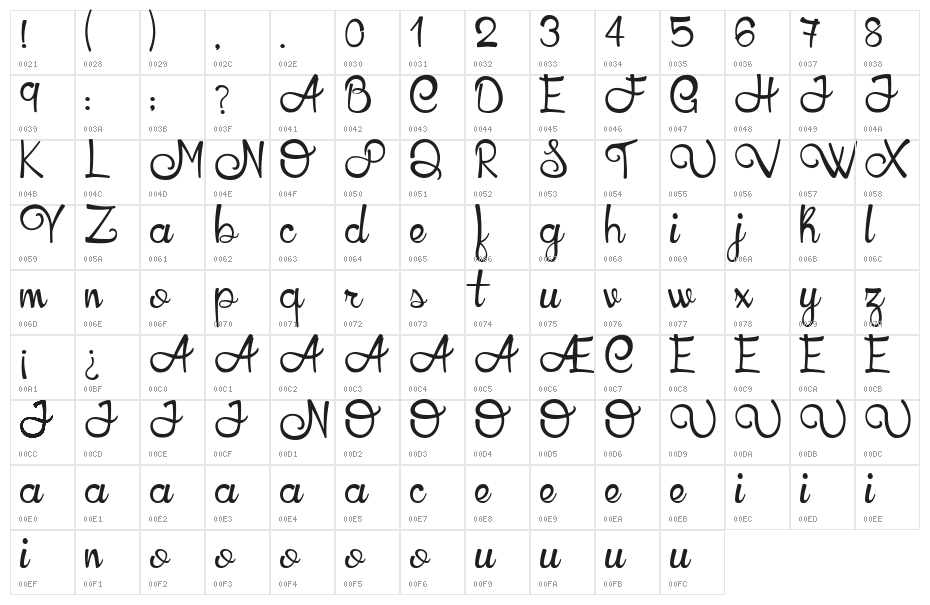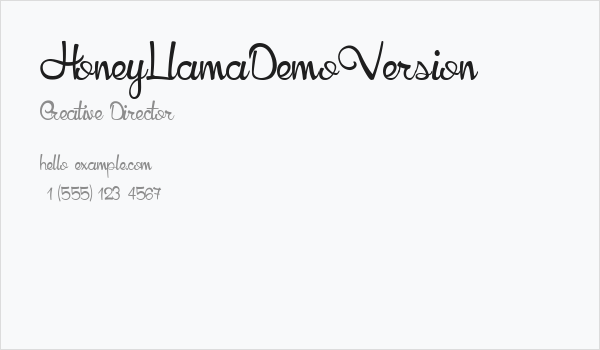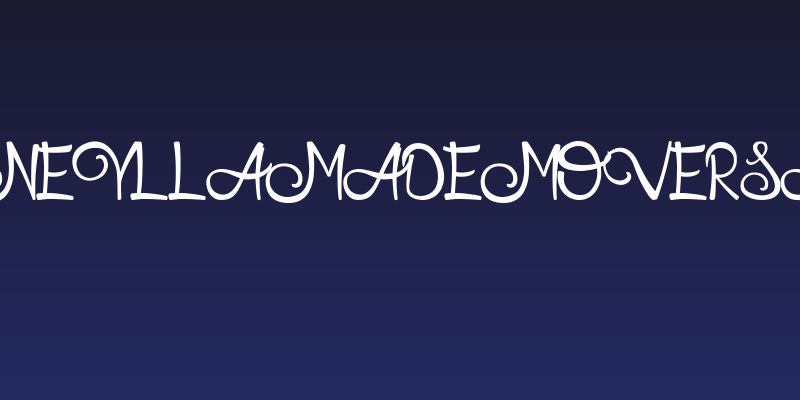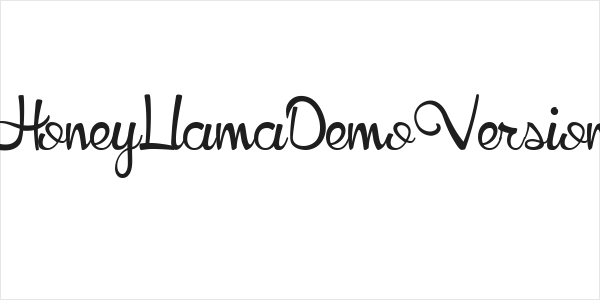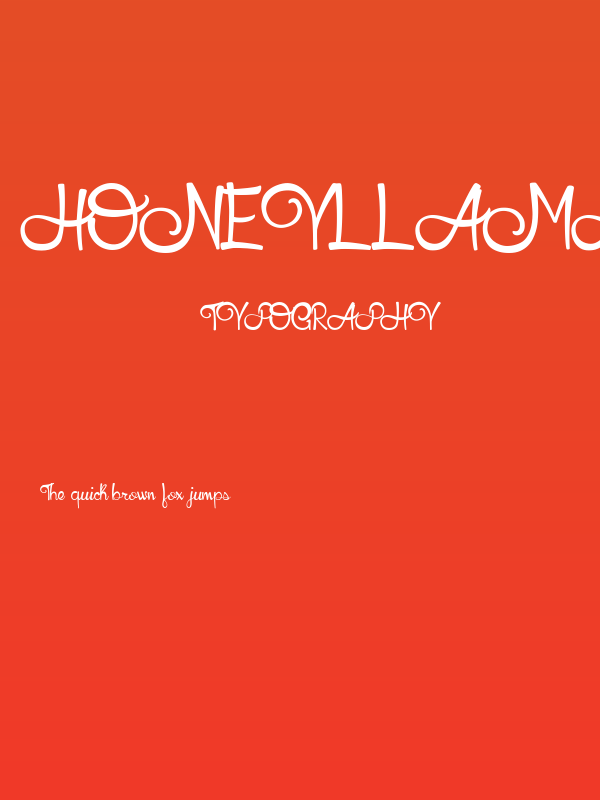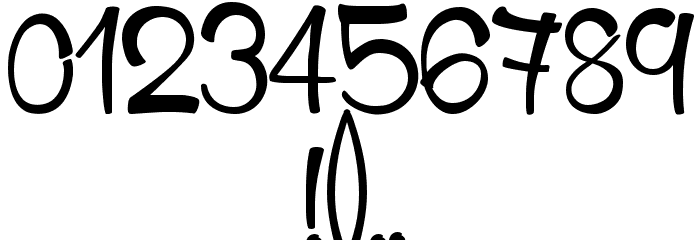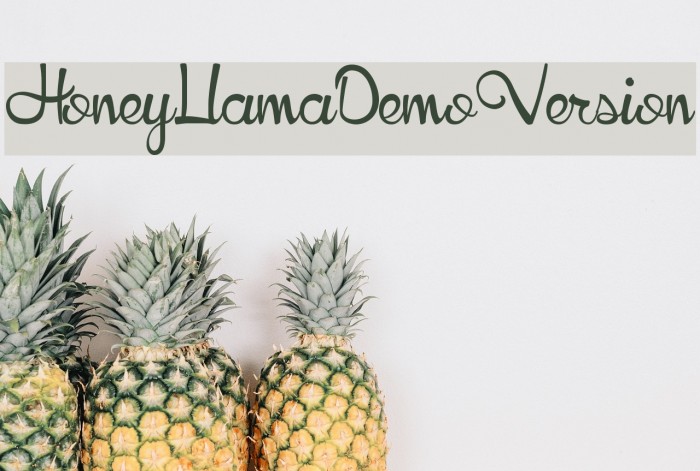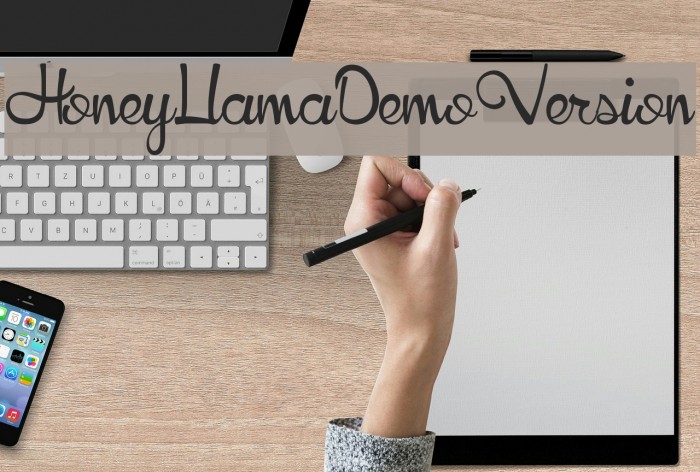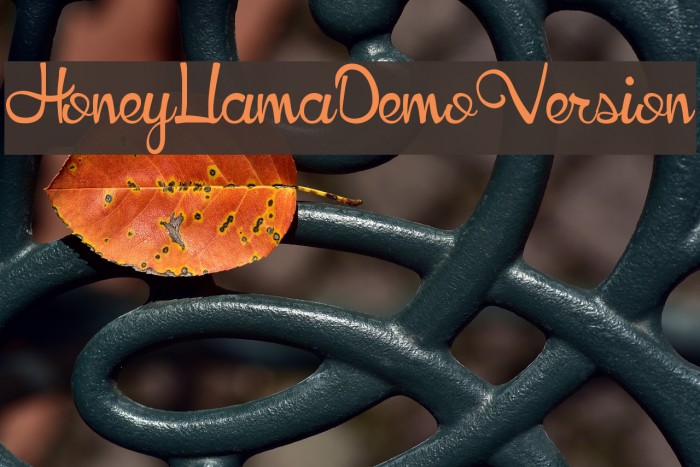
HoneyLlamaDemoVersion Font
Camilla Bertoni Berardi - www.behance.net/camillaberf9f1
| Anwendungsfall | Logos, Headlines, Creative projects |
| Vorgeschlagene Projekte | Ideal for greeting cards, invitations, playful branding, children's books, and creative posters. |